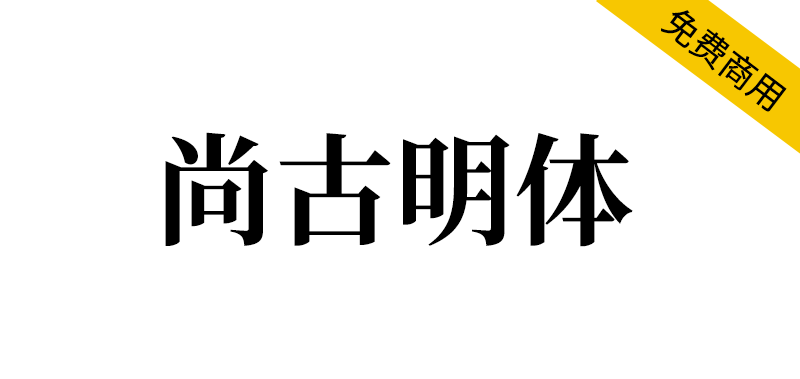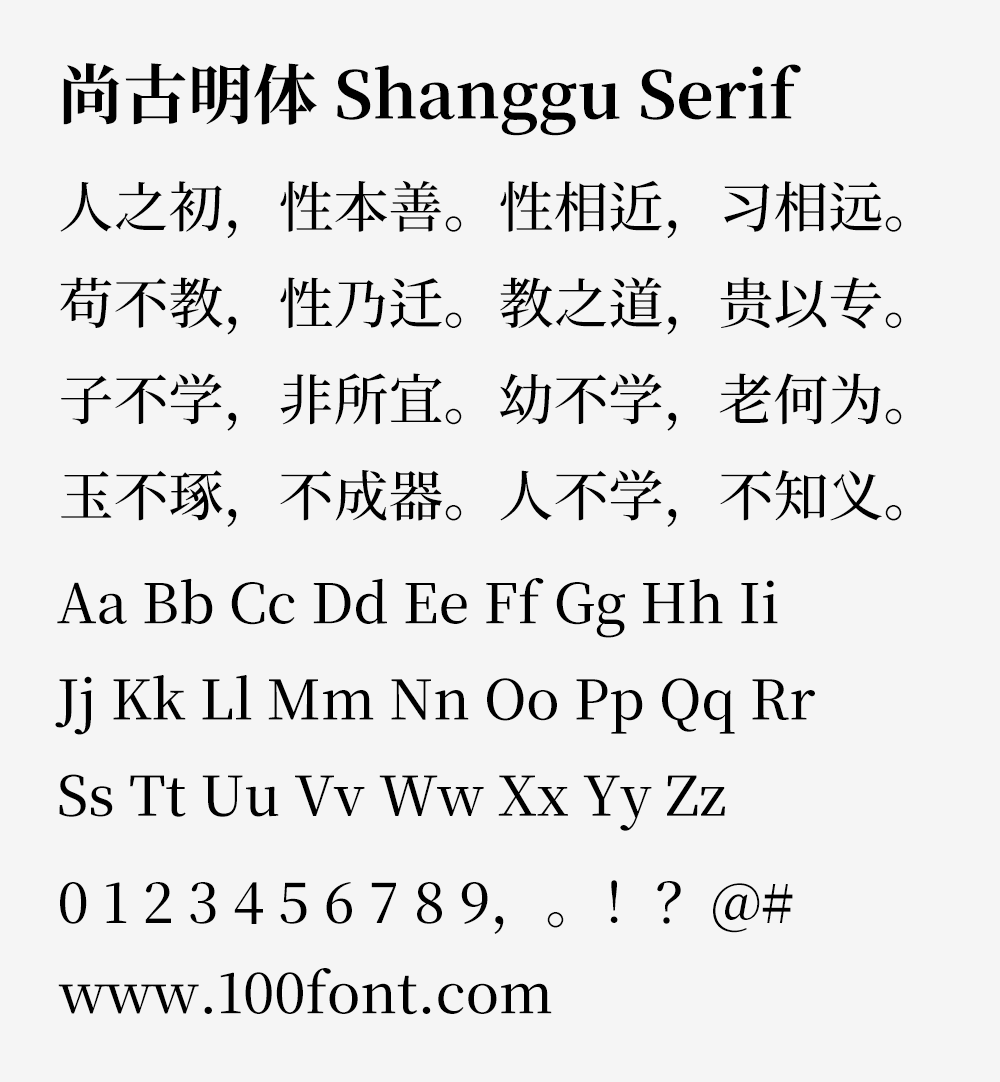
【尚古明体】基于思源的泛中日韩传承宋体字体
尚古字体是一套泛中日韩传承字形(旧字形),基于思源黑体思源宋体思源等宽以及思源系列衍生字型制作,包含黑体、明体、圆体等宽以及简转繁字型。
说明1:新旧异体字(如青-靑尚-尚兑-兑温-温等)合并为旧字形。
说明2:新旧异体字遵从Unicode分开编码,根据地区标点和简体字的不同,分为TC、SC、JP三种,字体名称中的TC、SC、JP仅代表地区标点的不同,本字体不使用地区的字形标准。
说明3:简转繁体,简入繁出的字体,可根据文字属性动态匹配一简多繁的情况(简转繁的意思就是输入简体字时会自动转换成繁体字)